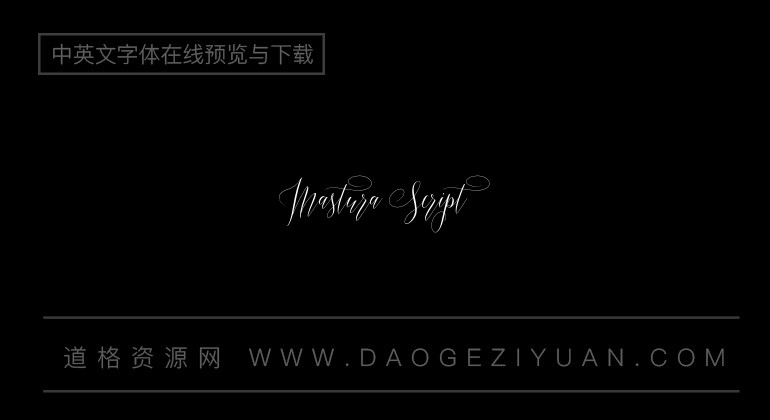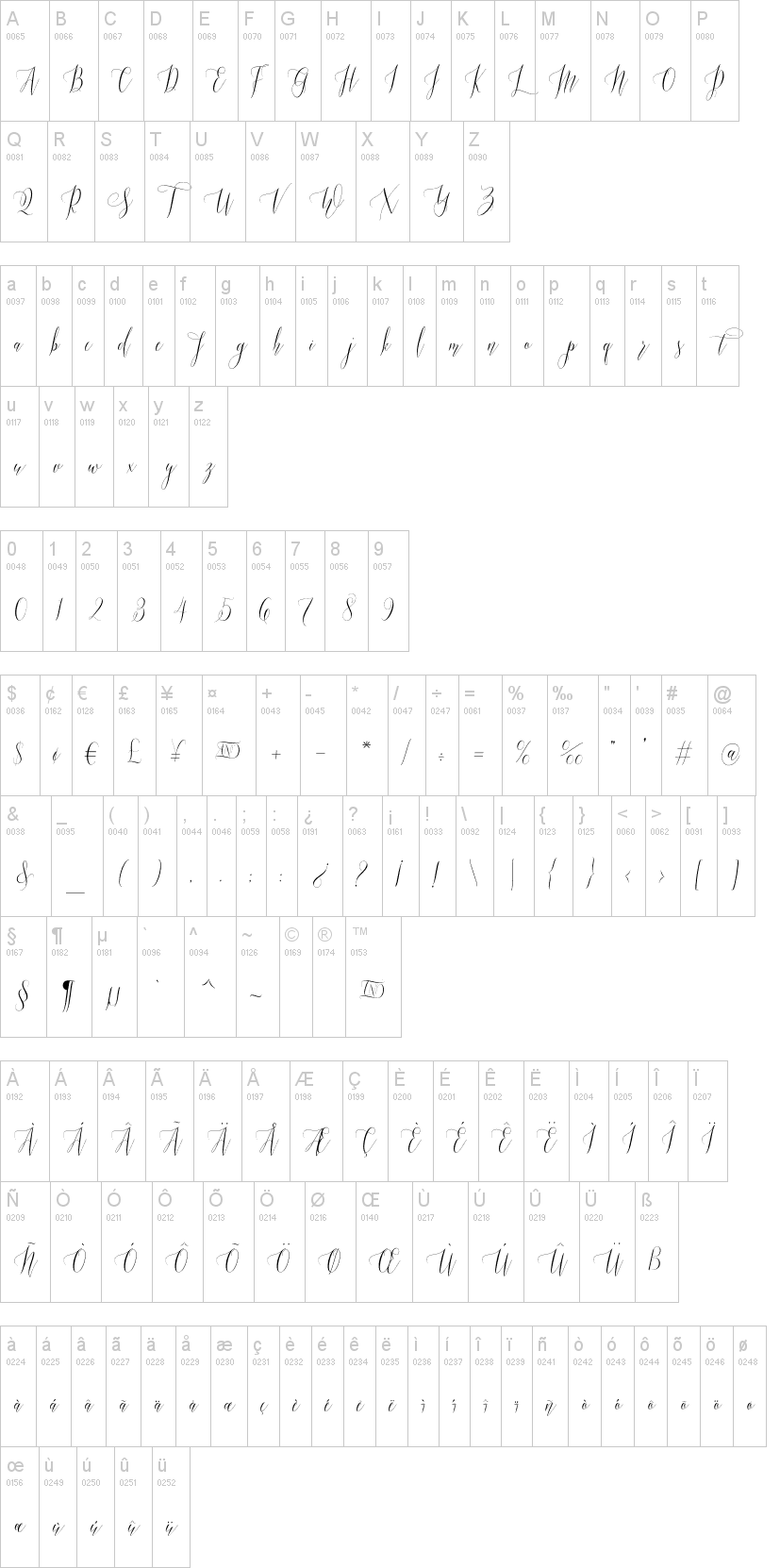
Mastura Script 字体是一种手写风格的字体,具有流畅和自然的笔画,让文本看起来更加生动和个性化。该字体由 Muhammad Faisal氏开发,通过Mastura Script 字体,您可以轻松地添加手写效果的文本和标题,使它们看起来更加艺术和手工制作。该字体适用于多种设计项目,如海报、卡片、包装、标志和广告等。Mastura Script 字体包含有大写字母、小写字母、数字和标点符号等,可以通过多种软件和应用程序使用,如Adobe Photoshop、Illustrator、InDesign、Microsoft Word等。内容介绍
Mastura Script是一款非常不错的手写艺术字体,具有很好的视觉感,适合于文化类的宣传设计、商业类品牌的广告和产品包装设计以及个性化文字排版等较多场景。